Квадратные скобки в рукописном шрифте: как нарисовать пару
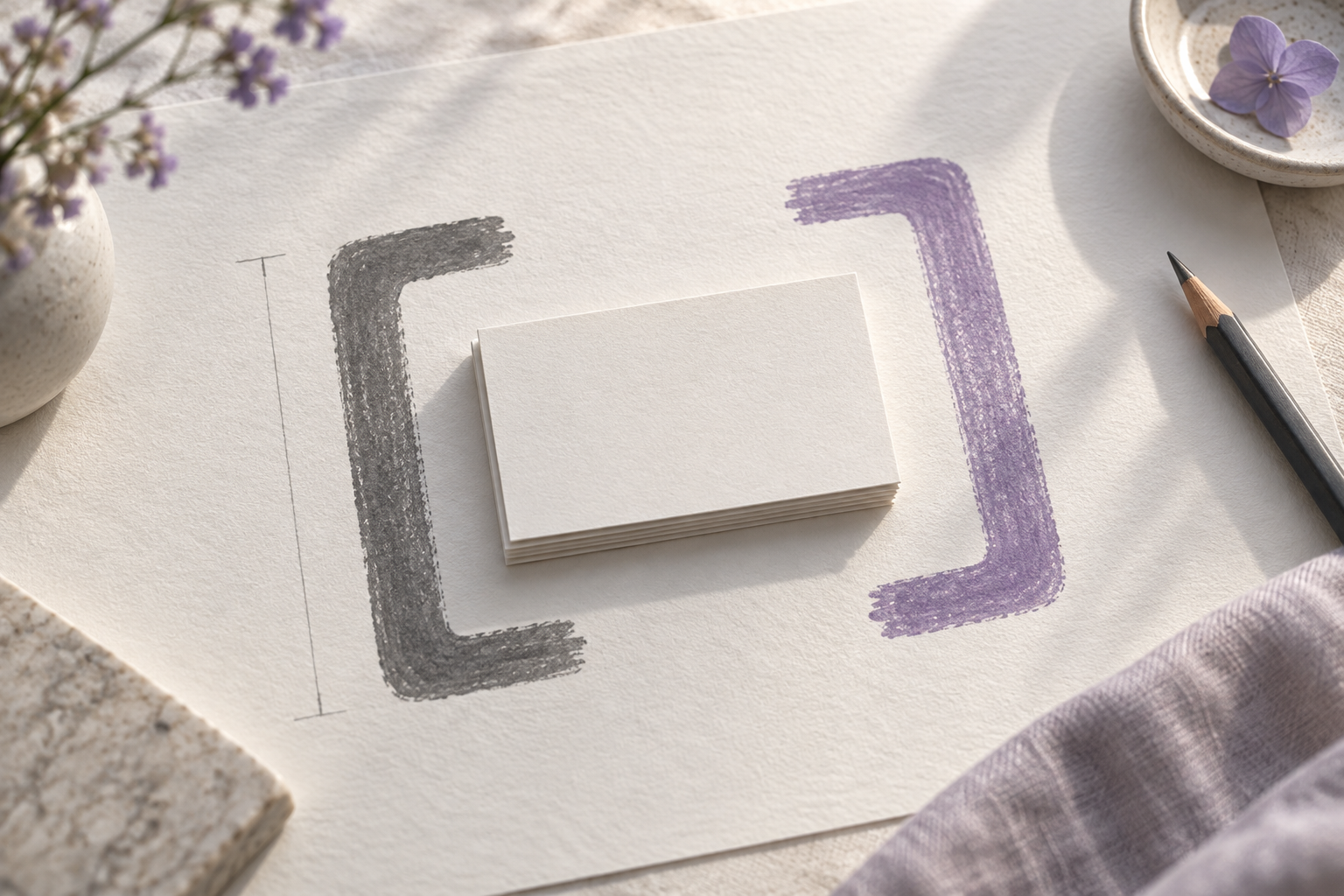
Квадратные скобки [ ] кажутся простыми: две вертикали и по короткому поперечному штриху. Но в собственном шрифте они часто выглядят как случайно обрезанные скобки, слишком тяжёлые углы или две одинаковые детали, которые не образуют пару. Чтобы знак был ясным, согласуйте ширину, высоту, толщину и положение углов, а затем проверьте обе формы в настоящих строках — от ссылки на источник до фрагмента кода.
Чем квадратные скобки отличаются от круглых и фигурных
У квадратных скобок есть два базовых знака: открывающая [ и закрывающая ]. Unicode называет их LEFT SQUARE BRACKET и RIGHT SQUARE BRACKET; это отдельные символы U+005B и U+005D. Такое различие важно на практике: визуально похожие квадратные скобки, круглые скобки и фигурные скобки не заменяют друг друга в тексте и должны оставаться отдельными знаками шрифта. Названия и кодовые точки можно сверить в таблице Unicode Basic Latin.
Круглая пара строится вокруг дуги, фигурная — вокруг встречных изгибов и узкой середины, а квадратная держится на прямом угле. Отдельно полезно посмотреть, как устроены круглые скобки в рукописном шрифте и фигурные скобки для кода и формул: это разные конструкции, а не варианты одного глифа. У рукописного рисунка угол может быть слегка мягким или неровным, но читатель всё равно должен быстро распознать вертикальную ножку и верхнюю с нижней полкой. Если верх и низ слишком короткие, знак похож на отдельный угол. Если они чрезмерно длинные, скобка начинает напоминать неполную рамку или букву.
Открывающая и закрывающая формы — не зеркальные копии на глаз. В паре [текст] внутренние концы полок смотрят друг на друга. При одинаковой толщине и длине поперечин направление лучше сначала проверить на крупных знаках, а затем — в мелком кегле, где одна неровность меняет характер всей пары.
С чего начать рисунок
Сначала определите, в каких текстах будет использоваться шрифт. В обычном наборе скобки встречаются в примечаниях, библиографических ссылках, индексах, математических выражениях, коде и заполнителях вроде [имя]. Для каждой задачи нужна узнаваемая пара, но не обязательно предельно технический вид. Если весь алфавит живой и рукописный, квадратные скобки могут сохранять жест пера; их не нужно превращать в безличные машинные прямоугольники.
Полезно задать три опорных размера относительно строчной буквы без выносных элементов:
- высоту скобок — обычно сравнивают с высотой прописной буквы и строчной «х», затем проверяют рядом с цифрами;
- толщину ножки — соотносят с основным вертикальным штрихом букв, чтобы знак не проваливался и не перетягивал внимание;
- длину полки — делают достаточной для чтения угла, но не настолько большой, чтобы она конфликтовала с соседним знаком.
Это не универсальные процентные нормы. В рукописном шрифте форма пера, наклон и контраст штриха отличаются, поэтому отправной размер следует оценивать по собственному алфавиту. Сначала нарисуйте пару чуть крупнее, чем предполагаемый итог, и отметьте базовую линию, верхнюю границу и оптический центр. После этого уменьшите изображение до рабочего масштаба: именно так будет видно, какие детали сохраняются без увеличения.
Как согласовать левую и правую скобку
Зафиксируйте общую конструкцию
Наметьте направляющие для высоты, базовой линии и двух крайних точек. У открывающей скобки вертикаль располагается слева, у закрывающей — справа. Верхняя и нижняя полки поворачивают к внутренней части пары. Выберите единый угол поворота, характер окончания штриха и радиус смягчения: если одна скобка почти прямоугольная, а другая заметно округлена, пара распадается.
Затем сравните не отдельные очертания, а расстояние между знаками. В сочетании [слово] внутренние углы создают небольшую визуальную нишу. Слишком длинные полки сужают её, короткие — растворяют угол. Оставьте место для букв и пробелов по бокам: знак не должен касаться содержимого, но и не должен отходить настолько далеко, чтобы казаться рамкой другого слова.
Учитывайте движение руки
При ручном рисунке вертикаль может немного наклоняться, а горизонтальная полка — подниматься в направлении движения. Это характер почерка, пока обе стороны остаются родственными. Сравните наклон ножек и направление полок с похожими штрихами в буквах и фигурных скобках. Не исправляйте каждую живую неровность до механической симметрии: цель — устойчивое узнавание, а не идеальная геометрия.
Проверьте силу нажима на повороте. Если там образуется тёмный узел, облегчите соединение: можно сократить перекрытие штрихов, смягчить угол или увести начало полки на долю толщины штриха. Если угол исчезает после уменьшения, не лечите проблему только удлинением полки. Иногда лучше сделать ножку яснее или уменьшить внутреннее скругление.
Оставьте паре согласованную ширину
Ширина открывающего и закрывающего знака не обязана совпадать математически. Важнее, чтобы вместе они создавали ровное обрамление. Если левая скобка широкая, а правая узкая, слово визуально съезжает; если обе слишком широки, запись начинает напоминать таблицу. Ставьте парные знаки рядом с узкими буквами («и», «л»), широкими («м», «ш») и цифрами. Одна и та же ширина рядом с разным содержимым воспринимается по-разному.
Квадратные скобки получаются убедительными, когда левая и правая формы согласованы, но сохраняют живой жест руки. Определите направляющие, проверьте длину полок и просветы, а затем прогоните пару через реальные примеры и уменьшенный размер. Для собственного шрифта можно подготовить шаблон с нужными знаками в Fontgenerator, а перед экспортом сравнить пробу на экране и на бумаге.